为任何设计项目选择字体可能会很麻烦。一些设计师默认为每个项目使用他们愿意使用的少数几种字体。其他人则花费数小时试图找出适合该项目的字体,而对最终选择却没有真正的信心。考虑到存在超过一百万种字体,这很正常。
正确的字体可以进行设计,而错误的字体则可以破坏设计。实验和实践对于掌握字体选择都很重要。但是,设计师可以记住一些要点,以使字体选择更加容易和集中。
范围
该项目的范围,其中的字体将被使用时,设计师首先应该考虑的事情之一。仅在有限范围内使用的字体将比在品牌的整个视觉效果中使用的字体具有较低的灵活性。
设计师应该考虑字体是仅用于数字项目还是用于印刷。他们还应该考虑字体是在有限时间内使用还是无限期使用。在选择新字体时,列出字体将用于的所有潜在项目可能会很有帮助。
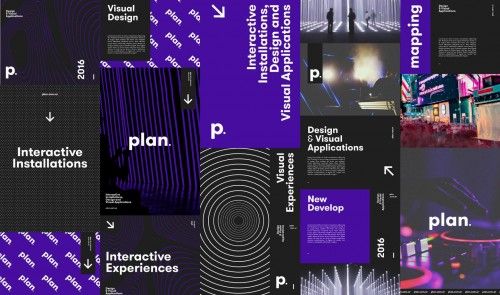
情绪
每个项目都有心情。那种心情是正式的还是非正式的,有趣的还是严肃的,现代的还是经典的,或者完全是其他的。就像每个项目一样,每种字体都有一种情绪。
对于设计师而言,重要的是要考虑项目的气氛以及他们正在考虑的字体如何增强或与这种气氛发生冲突。例如,在一家律师事务所的网站上使用Comic Sans会发生冲突。像Crimson Text或Helvetica之类的字体会更好。
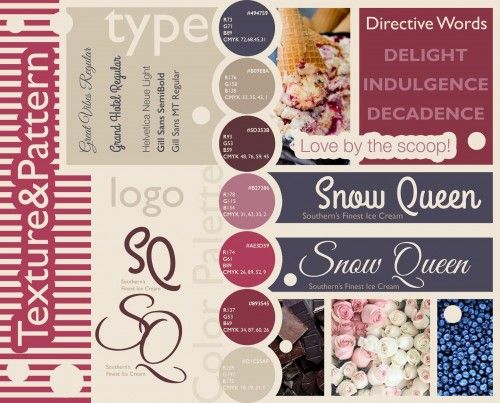
功能性
并非每种字体在每种重量和尺寸下都看起来不错。较大尺寸的显示较小尺寸字体时变得难以辨认。如果在显示尺寸下使用,在正文中以小尺寸显示的字体看起来有时会显得太平淡甚至无聊。
不过,有些字体实际上可以在任何大小上看起来都不错。设计师应该测试他们考虑使用的每种字体的字体,他们可以使用这些字体以确保它们可读性并且不会对UX产生负面影响。
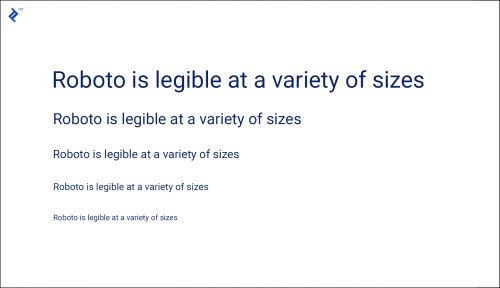
多功能性
完美适合在网络上使用的字体可能无法很好地翻译成印刷品,反之亦然。像格鲁吉亚这样的字体专门为在低分辨率屏幕上的可读性而设计,不像Book Antiqua这样的字体适合打印作业。
如果字体仅用于单个项目,则很容易确定打印功能或屏幕功能是最重要的。但是对于可能在多个项目中使用的字体,设计人员应确保该字体在可以使用它的每种媒介中都可以使用。
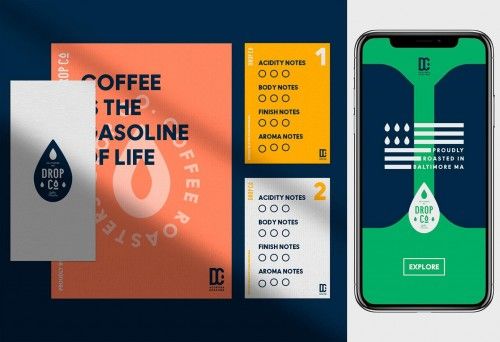
形象
该项目的形象(无论是幻灯片还是品牌的视觉形象)对于确定要使用的最佳字体至关重要。如果形象很严肃,字体也应该很严肃,反之亦然。
错误的字体可能会完全破坏品牌的形象。例如,在历史协会网站的设计中使用像Open Sans这样的现代内容并不能真正增强信息的准确性。像深红文本这样的字体会更好。
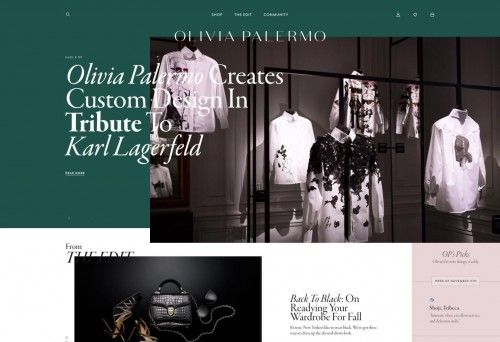
可读性
可读性可以说是字体的最重要特征。由于使用type来传达消息,因此如果无法读取该消息,则表明字体工作失败。
易读性和可读性并不完全相同。易读性是指区分字体中的字母形式有多容易。可读性又向前迈进了一步,指的是区分和阅读不同单词的难易程度。
所用字体的大小会极大地影响易读性和可读性。看起来不错的18像素字体可能无法识别10像素。除非设计者知道字体需要以较小的尺寸使用,否则这不一定会破坏。
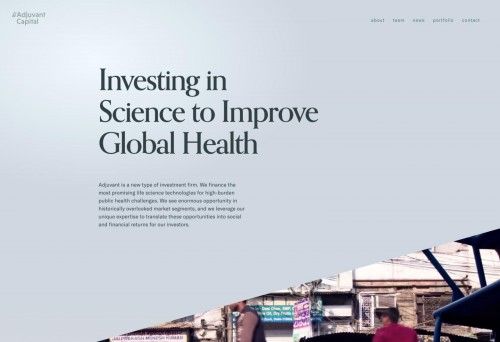
语言能力
并非每个网站或设计项目都会被翻译成多种语言。但是,在项目开始时确定是否可能进行翻译是一个好主意。并非所有字体都支持特殊字符(如带重音符号的字符),更不用说西里尔字母和希腊字母了。
在几乎所有项目中,重要的是,字体必须至少用于支持扩展的拉丁字符,例如重音符号和变音符号。由于不支持重音而无法拼写单词或名称,这会使项目看起来是不专业的。
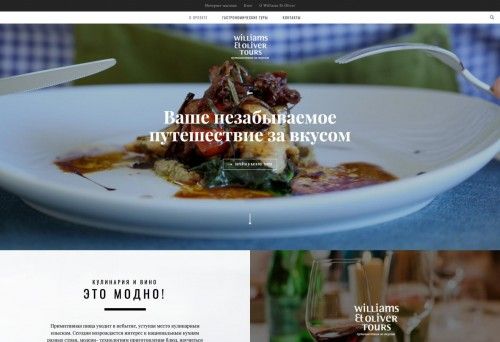
样式
有四种基本字体样式:衬线,无衬线,显示和脚本。衬线字体通常被视为更为传统和正式(尽管并非全部)。无衬线字体可以看作是更现代,更简约的字体。显示字体不适合小尺寸使用,但是它们的外观差异很大。脚本字体类似于手写或书法。脚本字体和显示字体都主要用于文本的简短块或标题和标题之类。
为了提高可读性,衬线字体曾经被认为在印刷中对读者更友好,而无衬线字体在屏幕上被视为对读者更友好。但是,两种风格的大多数现代字体都可以在任何一种媒体上很好地工作,尤其是随着屏幕分辨率的提高。
设计师应考虑是否要在其标题和标题中使用显示字体或脚本字体,并确定衬线或无衬线字体更适合其信息和项目品牌。这样做可以缩小设计师的字体选择范围,从而使最终选择更加容易。
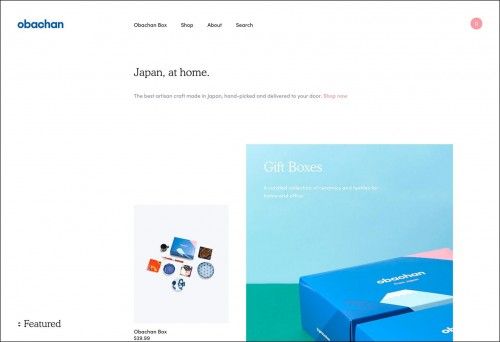
品牌
每个品牌都有一种心情和信息。重要的是,所有视觉元素(不仅是字体)必须匹配并支持该品牌希望给公众的印象。
根据品牌适用性来缩小字体选择范围可以从创建代表品牌的关键字列表开始。从那里,设计人员可以搜索包含那些关键字或同义词的字体。
例如,如果一个品牌是正式的和传统的,那么Garamond或Caslon之类的字体将是一个很好的选择。如果一个品牌是现代和前沿的,设计师可能会选择Roboto或Raleway之类的字体。
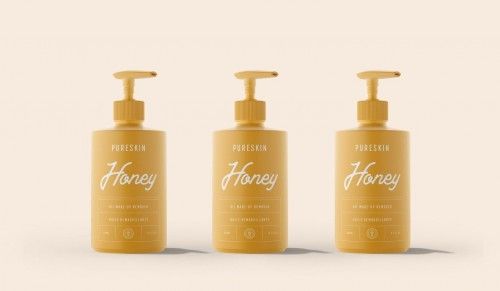
组合方式
并非所有字体都能与其他字体很好地配合使用。一些字体足够中性,可以与数百种其他字体配对。但是其他人具有如此独特的特征,以至于适当的组合受到限制。
两者都有优点。有限的组合可以更快地找到合适的组合,因为设计师可能只有十几种可供选择。但是拥有更多选择可以为将来的项目提供更大的灵活性。选择字体组合既是一门艺术,也是一门科学,需要设计师进行大量的实验和实践。
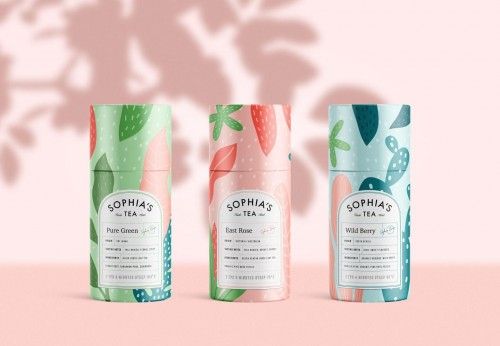
大字体家族
具有多个权重和样式的大型字体家族(例如Roboto或Baskerville)可以使设计人员更轻松地创建复杂的字体设计,而无需弄清楚哪些字体可以很好地协同工作。一些较大的字体家族甚至包括衬线和无衬线版本,这为设计人员提供了更大的灵活性。
在诸如品牌视觉形象的长期项目中,较大的字体家族也提供了更多的多功能性。能够根据确切的项目需求在多个权重或样式之间切换,从而为设计师提供了更大的灵活性,而不必偏离品牌的既定身份。
如何选择正确的字体
在任何设计项目中牢记这些技巧可以使字体的选择过程更加顺畅。想要提高选型技巧的设计师可以从事实践项目,例如为知名品牌或虚构项目选择新字体。然后,当面对现实世界的项目时,他们将对自己的技能和选择更有信心。
透彻了解每个项目的含义,可使设计人员更好地了解哪种字体最适合这些需求。一旦确定了项目的范围,其他考虑因素(例如情绪,多功能性,信息和品牌)便可以指导设计师选择最佳字体。可读性,功能和语言支持等其他考虑因素也可以帮助设计师进一步优化这些选择,以找到适合其设计工作的理想字体。